文字(字体)是人类文化的重要组成部分。无论在何种视觉媒体中,文字和图片都是其两大构成要素。文字排列组合的好坏,直接影响其版面的视觉传达效果。因此,文字设计是增强视觉传达效果,提高作品的诉求力,赋予作版面审美价值的一种重要构成技术。
在计算机普及的现代设计领域,文字的设计的工作很大一部分由计算机代替人脑完成了(很多平面设计软件中都有制作艺术汉字的引导,以及提供了数十上百种的现成字体)。但设计作品所面对的观众始终是人脑而不是电脑,因而,在一些需要涉及人的思维的方面电脑是始终不可替代人脑来完成的,例如创意、审美之类。
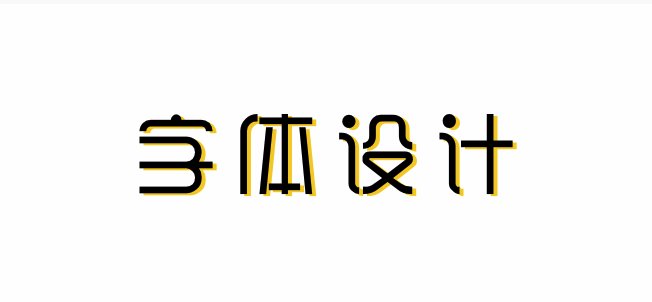
在这里,想谈一谈在平面设计中文字设计的几条原则及文字的组合应注意的几点。特别提醒一下,这应该是人脑完成的工作,电脑是无法代替的。
一、文字设计的原则
1. 文字的可读性:
文字的主要功能是在视觉传达中向大众传达作者的意图和各种信息,要达到这一目的必须考虑文字的整体诉求效果,给人以清晰的视觉印象。因此,设计中的文字应避免繁杂零乱,使人易认,易懂,切忌为了设计而设计,忘记了文字设计的根本目的是为了更好,更有效的传达作者的意图,表达设计的主题和构想意念。
2. 赋予文字个性:
文字的设计要服从于作品的风格特征。文字的设计不能和整个作品的风格特征相脱离,更不能相冲突,否则,就会破坏文字的诉求效果。 一般说来,文字的个性大约可以分为以下几种:
(1) 端庄秀丽。这一类字体优美清新,格调高雅,华丽高贵。
(2) 坚固挺拔。字体造型富于力度,简洁爽朗,现代感强, 有很强的视觉冲击力。
(3) 深沉厚重。字体造型规整,具有重量感,庄严雄伟,不可动摇。
(4) 欢快轻盈。字体生动活泼, 跳跃明快, 节奏感和韵律感都很强, 给人一种生机盎然的感受。
(5) 苍劲古朴。这类字体朴素无华, 饱含古韵, 能给人一种对逝去时光的回味体验。
(6) 新颖独特。字体的造型奇妙,不同一般,个性非常突出,给人的印象独特而新颖。
3.在视觉上应给人以美感:
在视觉传达的过程中,文字作为画面的形象要素之一,具有传达感情的功能,因而它必须具有视觉上的美感,能够给人以美的感受。字型设计良好,组合巧妙的文字能使人感到愉快,留下美好的印象,从而获得良好的心理反应。反之,则使人看后心里不愉快,视觉上难以产生美感,甚至会让观众拒而不看,这样势必难以传达出作者想表现出的意图和构想。
4.在设计上要富于创造性:
根据作品主题的要求,突出文字设计的个性色彩,创造与众不同的独具特色的字体,给人以别开生面的视觉感受,有利于作者设计意图的表现。设计时,应从字的形态特征与组合上进行探求,不断修改,反复琢磨,这样才能创造出富有个性的文字,使其外部形态和设计格调都能唤起人们的审美愉悦感受。
文字的组合
文字设计的成功与否,不仅在于字体自身的书写,同时也在于其运用的排列组合是否得当。如果一件作品中的文字排列不当,拥挤杂乱,缺乏视线流动的顺序,不仅会影响字体本身的美感,也不利于观众进行有效的阅读,则难以产生良好的视觉传达效果。要取得良好的排列效果,关键在于找出不同字体之间的内在联系,对其不同的对立因素予以和谐的组合,在保持其各自的个性特征的同时,又取得整体的协调感。为了造成生动对比的视觉效果,可以从风格、大小、方向、明暗度等方面选择对比的因素。
但为了达到整体上组合的统一,又需要从风格、大小、方向、明暗度等方面选择协调相同的因素。 将对比与协调的因素在服从于表达主题的需要下有分寸的运用,能造成既对比又协调的,具有视觉审美价值的文字组合效果。 文字的组合中,要注意以下几个方面: 1. 人们的阅读习惯 文字组合的目的,是为了增强其视觉传达功能,赋予审美情感,诱导人们有兴趣的进行阅读。因此在组合方式上就需要顺应人们心理感受的顺序。
下面,列出人们的一般阅读顺序。
1.水平方向上,人们的视线一般是从左向右流动;垂直方向时,视线一般是从上向下流动;大于45度斜度时,视线是从上而下的;小于45度时,视线是从下向上流动的。
2. 字体的外形特征 不同的字体具有不同的视觉动向,例如:扁体字有左右流动的动感,长体字有上下流动的感觉,斜字有向前或向斜流动的动感。因此在组合时,要充分考虑不同的字体视觉动向上的差异,而进行不同的组合处理。比如:扁体字适合横向编排组合,长体字适合作竖向的组合,斜体字适合作横向或倾向的排列。合理运用文字的视觉动向,有利于突出设计的主题,引导观众的视线按主次轻重流动。
3. 要有一个设计基调 对作品而言,每一件作品都有其特有的风格。在这个前提下,一个作品版面上的各种不同字体的组合,一定要具有一种符合整个作品风格的风格倾向,形成总体的情调和感情倾向,不能各种文字自成一种风格,各行其是。总的基调应该是整体上的协调和局部的对比,于统一之中又具有灵动的变化,从而具有对比和谐的效果。这样,整个作品才会产生视觉上的美感,符合人们的欣赏心理。 除了以统一文字个性的方法来达到设计的基调外,也可以从方向性上来形成文字统一的基调,以及色彩方面的心理感觉来达到统一基调的效果等等。
4. 注意负空间的运用 在文字组合上,负空间是指除字体本身所占用的画面空间之外的空白,即字间距及其周围空白区域。 文字组合的好坏,很大程度上取决于负空间的运用是否得当。 字的行距应大于字距,否则观众的视线难以按一定的方向和顺序进行阅读。 不同类别文字的空间要作适当的集中,并利用空白加以区分。 为了突出不同部分字体的形态特征,应留适当的空白,分类集中。
在有图片的版面中,文字的组合应相对较为集中。如果是以图片为主要的诉求要素,则文字应该紧凑地排列在适当的位置上,不可过分变化分散,以免因主题不明而造成视线流动的混乱。 创意是设计者的思维水准的体现,是评价一件设计作品好坏的重要标准。在现代设计领域,一切制作的程序由电脑代劳,使人类的劳动仅限于思维上,这是好事,省却了许多不必要的工序,为创作提供了更好的条件,但是,在某些必要的阶段上,还是不能完全让电脑来做,人,毕竟是人。